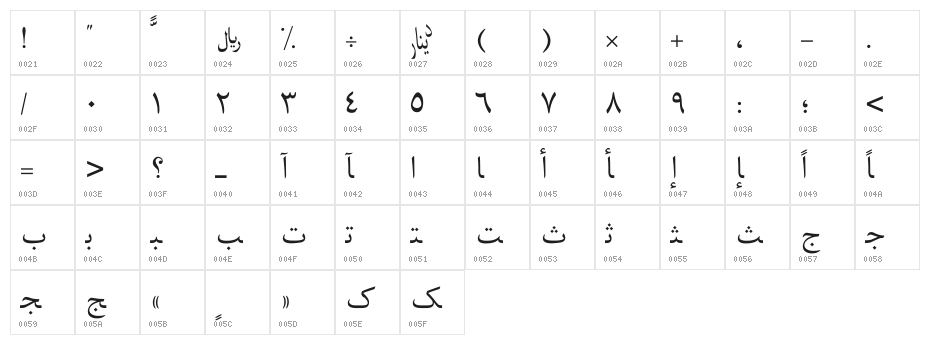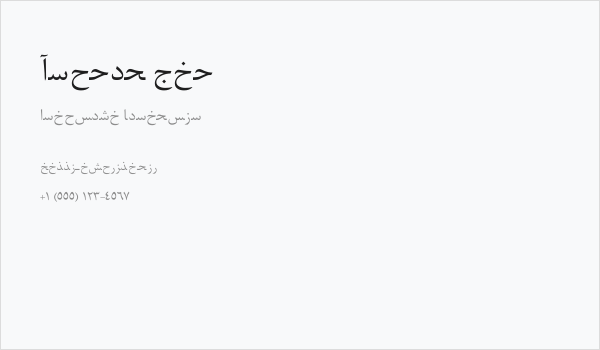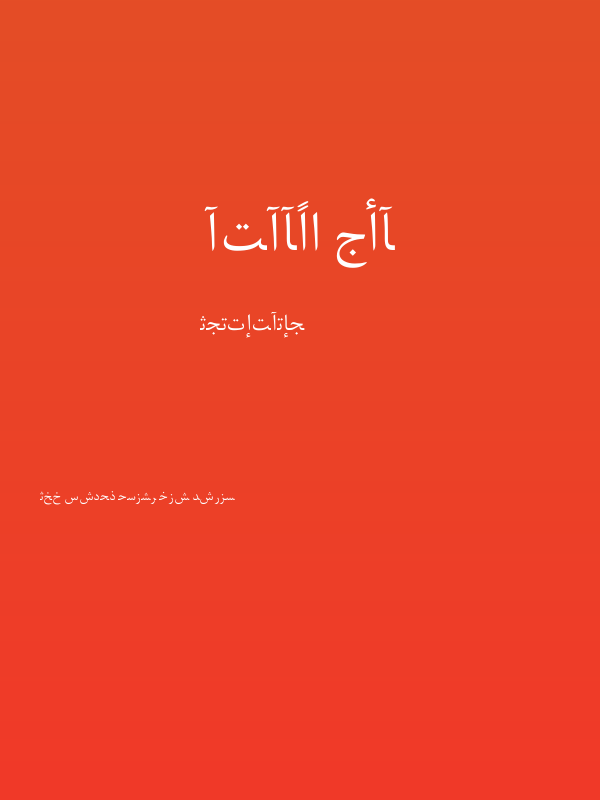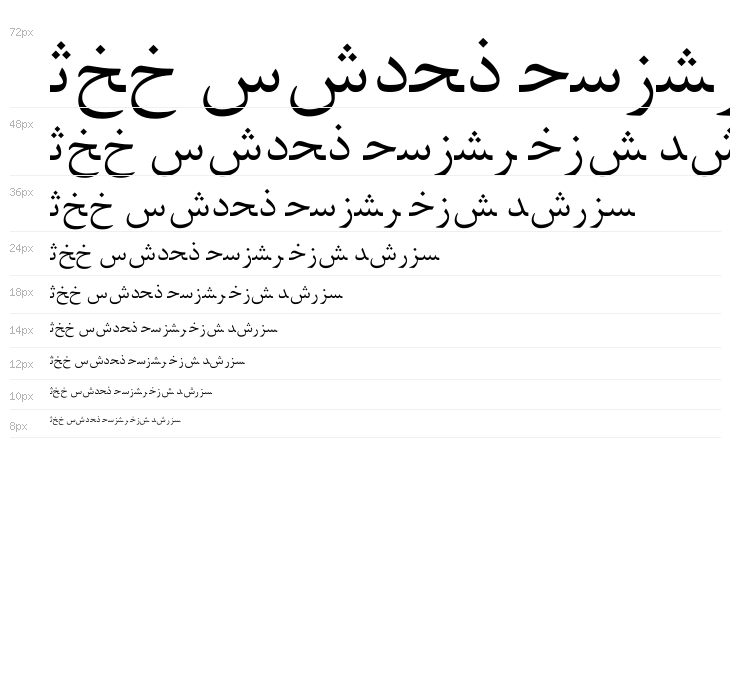
Arabic Web Font
| Область применения | Headlines, Body text, Logos |
| Рекомендуемые проекты | Ideal for branding, editorial design, signage, and digital content that requires a touch of elegance and cultural authenticity. |